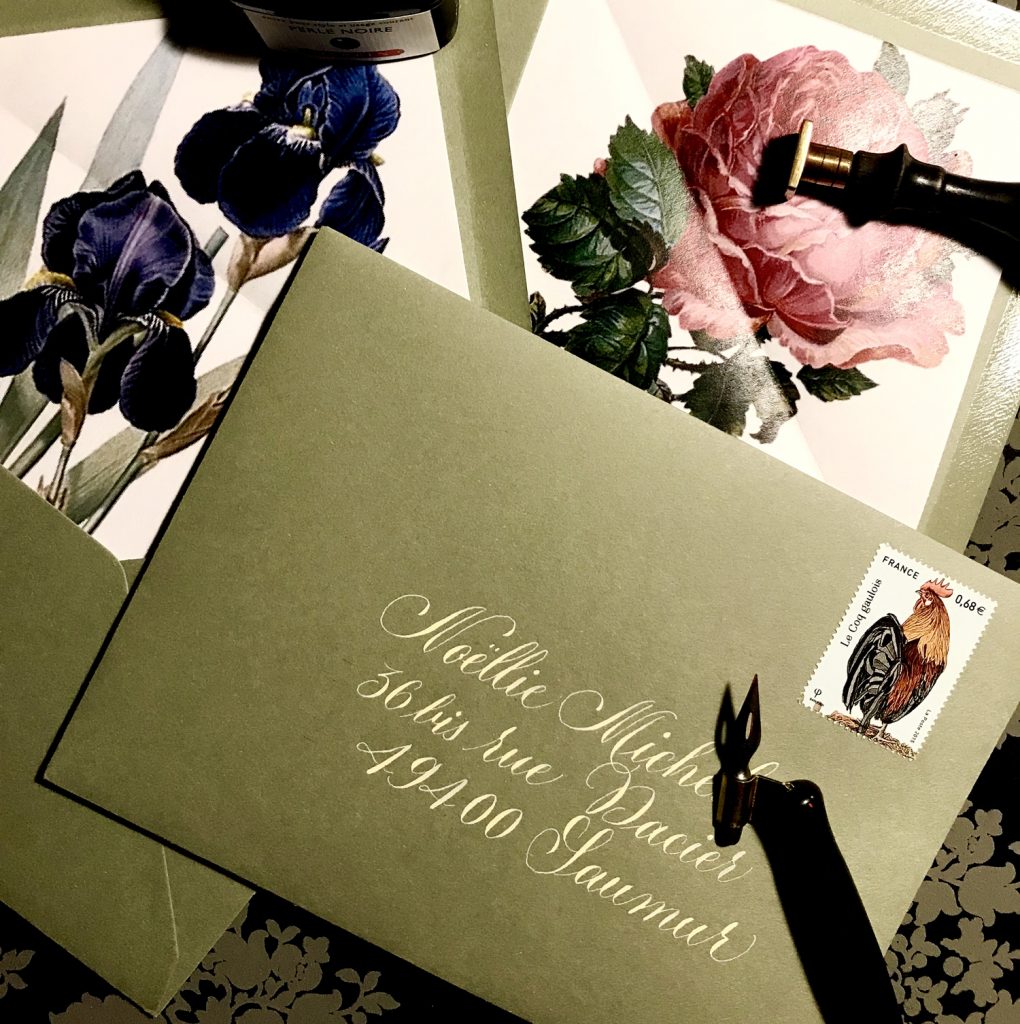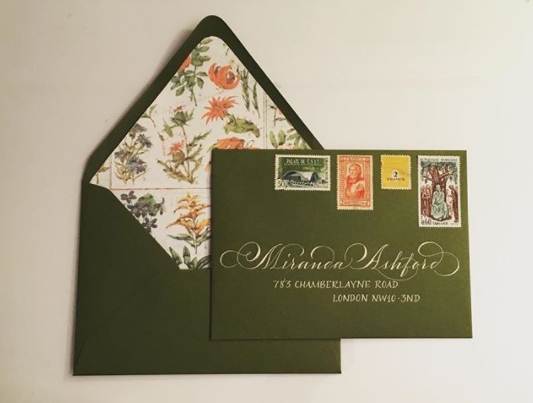
Comment créer une enveloppe personnalisée ?
Là, vous pensez peut-être que je vais vous proposer un super tuto qui va vous prendre des heures pour faire une carte et une enveloppe… que nenni ! Aujourd’hui, je vous propose juste une idée toute bête pour personnaliser des enveloppes dans un style très féminin et romantique. Au point de départ j’avais vu une magnifique enveloppe doublée sur le fil Instagram de Joy Fairclough, et je me suis demandée où diable elle avait l’avait trouvée !
Enveloppe réalisée par Joy Faiclough de StudioFrenchBlue
En cherchant, j’ai trouvé un tuto tout simple sur un blog américain, alors voici, il vous faut :
Enveloppe doublée
Enveloppe vierges de couleur et papier déco
• Une enveloppe : par exemple les Pollen de Clairefontaine, qui se déclinent dans de nombreuses couleurs
• Du papier avec de beaux motifs dessus : j’ai choisi des planches botaniques que j’ai imprimées sur une feuille A4. Simple et bon marché ! Vous pouvez prendre ce que vous avez sous la main, inutile d’acheter du papier exprès : des pages de magazine (découpez vos Flow, Respire et consorts…), des journaux, pourquoi pas du papier cadeau.
• Une règle et un crayon de papier
• Un cutter
• De la colle bâton ou du scotch double face
Étapes
1. Relever les dimensions de votre enveloppe ouverte
2. Tracez un gabarit sur votre feuille de motif, en retirant 1 cm sur les côtés et le bas, et 0.5 cm sur la hauteur
3. Découpez soigneusement, en faisant un petit arrondi sur la pointe
4. Glissez votre doublure dans l’enveloppe pour vérifier que c’est à la bonne taille et repliez le rabat.
5. Appliquez la colle, ou le scotch double face sur le rabat plié, et repliez le rabat de l’enveloppe dessus pour le fixer
6. Voilà, le tour est joué !
Pour la première enveloppe  : 10mn montre en main !
Enveloppes doublées botanique
Enveloppes doublées esprit botanique
Ecrire l’adresse
Vous pouvez écrire l’adresse à la plume, au brushpen, au stylo, peu importe. Ce qui va compter, c’est une belle écriture ! Entraînez-vous avant pour bien calibrer l’adresse et ne pas arriver en bout de ligne avec un mot à moitié écrit (c’est du vécu).
Éventuellement, écrivez préalablement l’adresse au crayon de papier avec un trait très léger, puis repassez dessus à la plume. Enfin, vous gommerez une fois l’encre sèche.
Normalement, sur les enveloppes de la gamme Pollen l’encre ne fuse pas. Cela ne dispense pas de sacrifier une de vos enveloppes pour faire un petit essai.
Ici, j’ai utilisé un mélange de gouache Blanc et Jaune de Naples.
Choisir de jolis timbres
Un beau timbre ajoutera une touche raffinée à vos enveloppes.
Rendez-vous dans votre bureau de poste et demandez quels sont les timbres qu’ils proposent en ce moment. Parfois, de belles surprises vous attendent ! Si votre bureau de Poste ne propose pas de beaux timbres, sachez que vous pouvez les commander en ligne sur la e-boutique de la Poste. D’ailleurs, les tarifs vont augmenter significativement en 2018. Donc c’est le moment de se faire une petite réserve de timbres à validité permanente.
Enfin, pour les parisiens, rendez-vous au Carré d’Encre, rue Duphot dans le 9ème, une superbe adresse qui propose un choix de timbres immense, mais aussi toute la papeterie pour réussir vos correspondances, des plumes de calligraphie, des encres…
Enveloppe calligraphiée
Enveloppe calligraphiée, timbrée, prête à poster